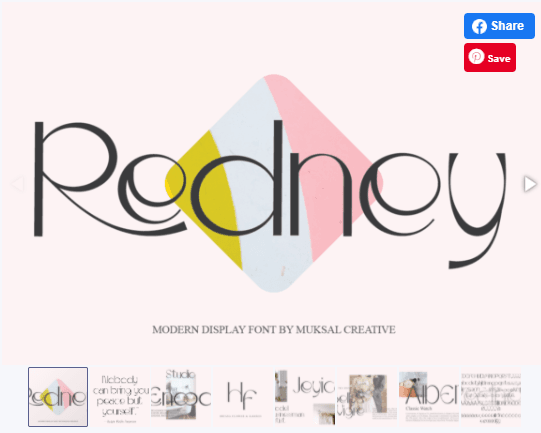
Redney Font
Redney - это современный гладкий шрифт без засечек. Созданный в элегантном стиле, этот прекрасный шрифт станет отличным дополнением к вашей библиотеке шрифтов, так как он может улучшить внешний вид любого творения!